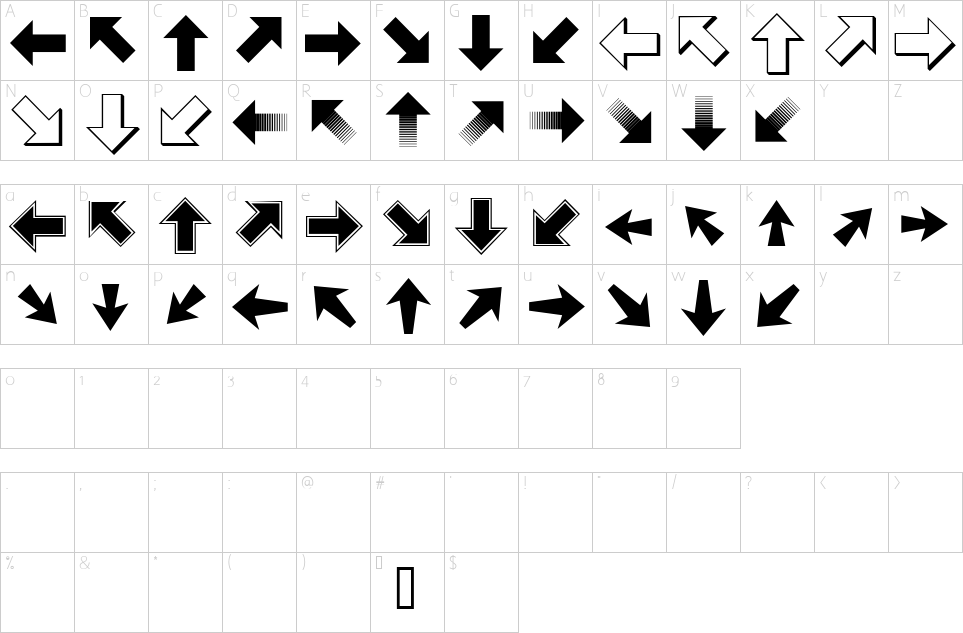
Aqui está uma descrição em português do Brasil, envolvente e natural, para uma página de download da fonte ‘Pizzadude Pointers Font | 1001 Free Fonts’: A fonte ‘Pizzadude Pointers’ é uma escolha perfeita para adicionar um toque de personalidade a suas criações digitais, especialmente se você gosta de um estilo divertido e descontraído. Desenhada pelo criativo Pizzadude, essa fonte oferece um design minimalista e lúdico, ideal para nomes de empresas, títulos de páginas web, ou qualquer outro aplicativo que você queira dar um toque especial. Com seu design simples, ‘Pizzadude Pointers’ é fácil de ler e de integrar em qualquer projeto, seja para uso em títulos ou subtítulos. Ela vem em versões para Windows e Mac, garantindo que todos os usuários possam acessar e aplicar a fonte com facilidade. Com mais de 6.857 downloads, é claro que muitos outros criadores já estão utilizando esta fonte de maneira positiva. Para qualquer profissional de design, seja profissional ou hobbyista, a ‘Pizzadude Pointers’ é uma excelente adição para seu arsenal de recursos. Essa fonte não apenas oferece uma solução prática e versátil, mas também adiciona um toque especial e único a qualquer projeto. Seja para um site, aplicativo ou impressão, ‘Pizzadude Pointers’ é uma fonte que se destaca e é certamente um investimento valioso.